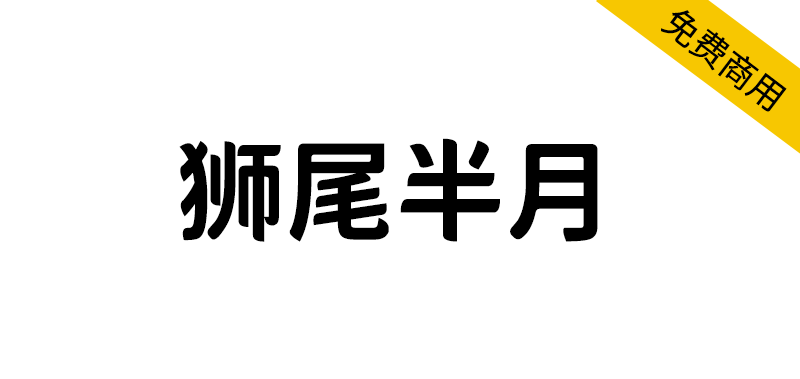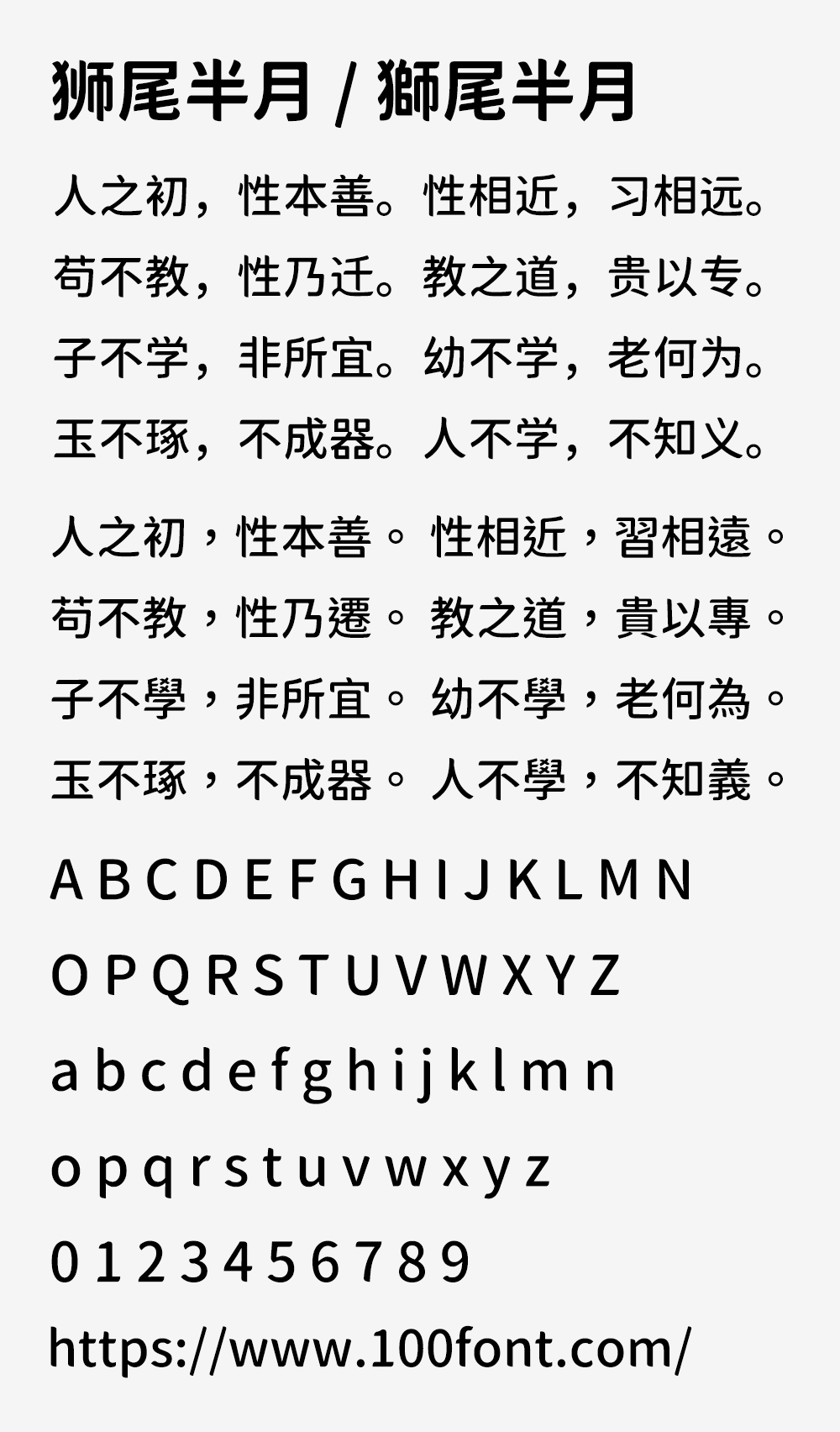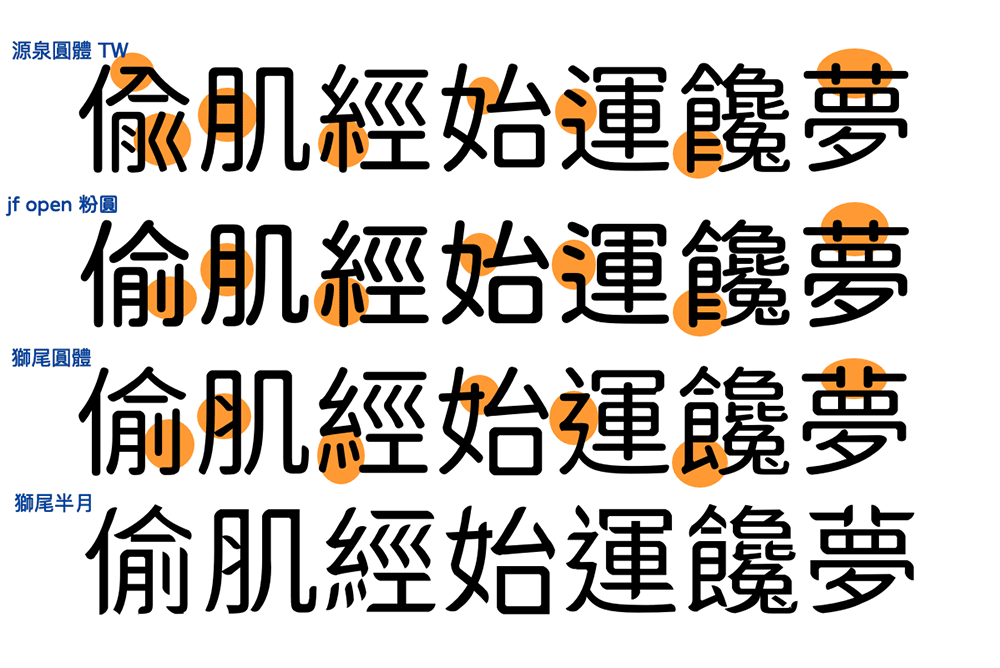
狮尾半月字体基于思源黑体的拔脚和加半圆改造,不圆也不方的字体,特色之一是「十」长的像忍者的手里剑。和思源黑体一样,有7种字重,支持简体中文、繁体中文、韩文与日文。
狮尾半月和狮尾牙膏圆体长像几乎一样。差别在「中」字中间的口,半月会变圆,牙膏是左上和右下是圆。单独遇到「口」部件时,2个字体有时是一样,有时方向会相反,狮尾牙膏圆体套用的规则比较明确。